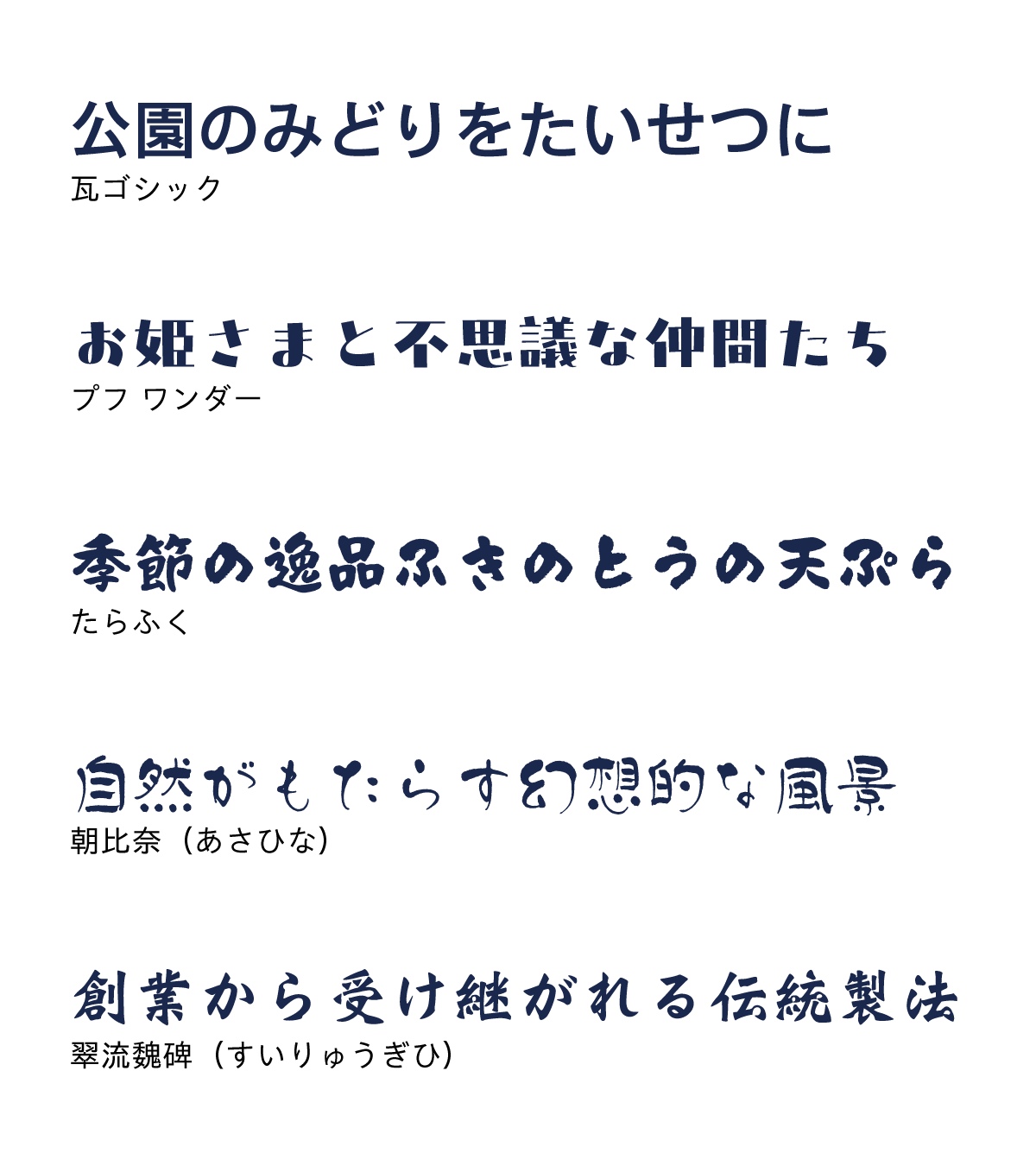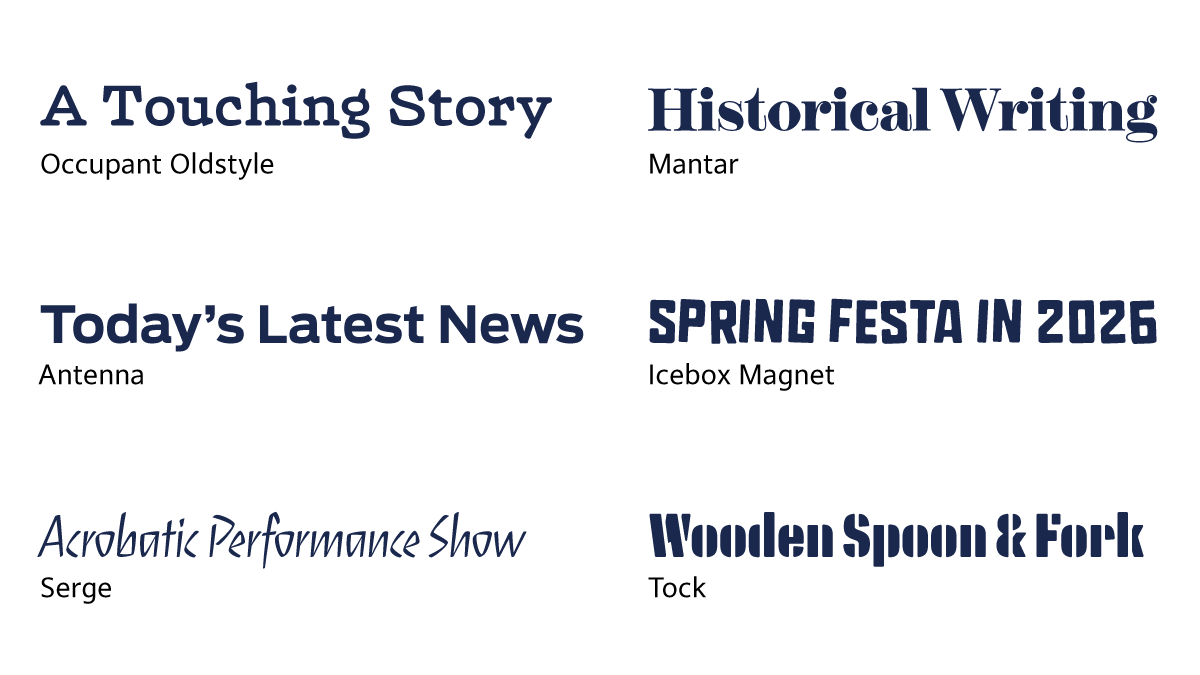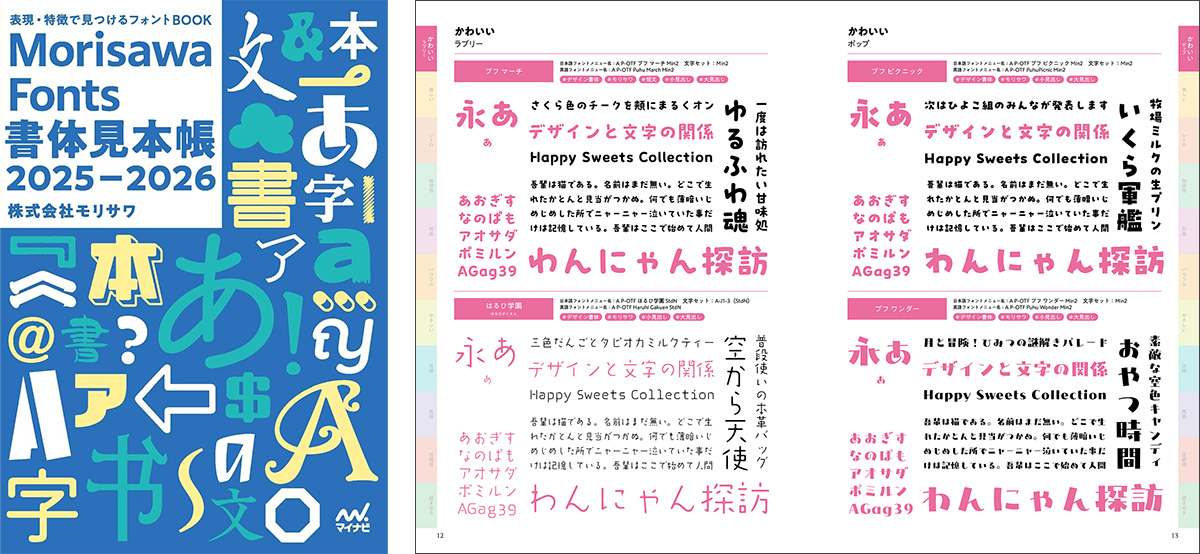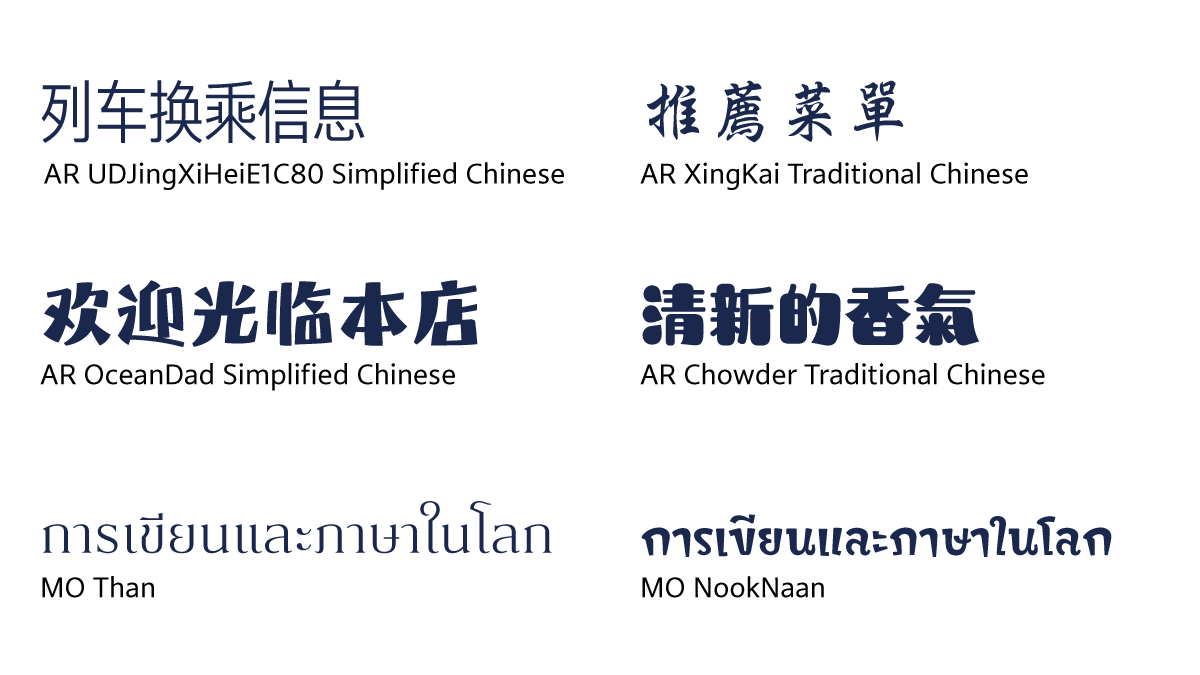
モリサワ 多彩な和文フォント、欧文・中国語・タイ文字など多言語フォントを含む、大ボリュームの新書体第2弾を2月12日より提供予定 〜使い手目線にこだわった最新版の見本帳も完成〜
第2弾のリリースでは、人気シリーズ「プフ」の新書体「プフ ワンダー」のほか「瓦ゴシック」「たらふく」などの和文フォント、欧文や中国語、タイ文字フォントが仲間入りします。2024年度からMorisawa Fontsにて提供しているOccupant Fontsの欧文フォントやArphic Typesの中国語フォントをはじめ、DB DesignとCadson Demakのユニークなタイ文字フォント、今回初めてMorisawa Fontsからリリースする上海印刷技術研究所の簡体字フォントも加えた、計103ファミリーのラインナップです。
新書体 2025–2026 第2弾
人気デザイン書体「プフ」シリーズの新書体も登場。多彩な和文フォント
和文フォントからは、2023年にリリースした毎日新聞社による開発書体「瓦明朝」のゴシック体シリーズである「瓦ゴシック」、2022年から好評いただいている「プフ」シリーズから新たに「プフ ワンダー」、書家による毛筆の文字が元となった「たらふく」「朝比奈(あさひな)」、中国の北朝時代の石拓の書に由来する字形やスタイルを取り入れた「翠流魏碑(すいりゅうぎひ)」をリリースします。
ますます充実する欧文、中国語、タイ文字フォント
欧文フォントは、2024年度よりMorisawa Fontsに仲間入りしたOccupant Fontsのライブラリがさらに充実します。ラウンデッドサンセリフや和文書体の明朝体から着想を得た穏やかな印象のセリフ体「Occupant Oldstyle」や、インダストリアルデザインを想起させる力強さとあたたかみを兼ね備えたサンセリフ体「Antenna」など、バラエティに富んだ計39ファミリー405フォントです。
また中国語フォントは、同じく2024年度よりMorisawa Fontsに加わったArphic Typesの簡体字・繁体字フォントに加え、今回新たに上海印刷技術研究所の簡体字フォントをリリースします。
Arphic Typesからは、行書や楷書といった筆書系の書体やデザイン書体を中心としたラインナップの29ファミリー68フォントをリリースします。
上海印刷技術研究所は、現代の中国国内において広く使用されている印刷書体を生み出した歴史あるファウンダリーで、このたび4ファミリーをリリースします。
さらに、タイ文字のフォントとして、2016年から提供を開始しているDB DesignとCadson Demakのフォントも大幅拡充します。ベーシックなスタイルから、ペンで手書きをしたような書体やジオメトリックなデザイン書体といったユニークな書体も充実した計26ファミリー83フォントが新たにお使いいただけるようになります。
Morisawa Fonts書体見本帳2025–2026
新書体2025–2026を掲載した書体見本帳「表現・特徴で見つけるフォントBOOK Morisawa Fonts書体見本帳2025–2026」が完成しました。今後、モリサワが参加する各イベントでお渡しするほか、全国の書店でも特製カバーつき別装丁版をお買い求めいただけます。